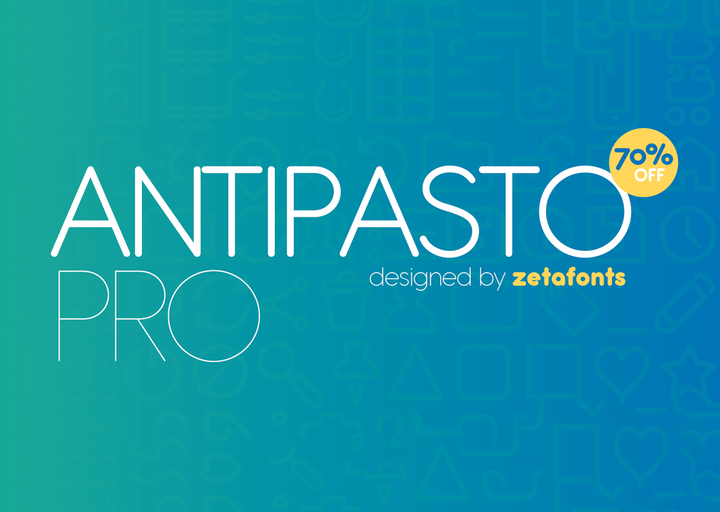
Aqui está uma descrição em português para a página de download da font Antipasto Pro Font Family: Antipasto Pro é uma nova família de fuentes gregas e cílinicas, com cinco pesos diferentes que vão desde o fino até o extrabold. Esta é a versão revista e ampliada do original lançado em 2017 pelo designer Cosimo Lorenzo Pancini. O conjunto completo agora inclui caracteres cílindricos e gregos, além de recursos typográficos avançados como minúsculas grandes e numerais antigos. Antipasto Pro também oferece 8 pesos diferentes para seus icônicos, tornando-o um recurso de design extremamente versátil. Com sua geometria pura e simplicidade, a família gera um visual moderno e eficaz sem perder seu charme distintivo. É perfeito para ambientes onde você precisa de uma fonte legível e elegante, seja em sites ou aplicativos de mídia social. Seja para design editorial ou criação de logotipos, Antipasto Pro trará um toque moderno à sua próxima peça de arte. Ao longo do tempo, a família foi ampliada e revisada com o objetivo de atender às necessidades dos designers gráficos contemporâneos. Com o antepassado original reavaliado e atualizado em 2017, Antipasto Pro é uma escolha ideal para quem busca um estilo moderno que se adapta a diferentes ambientes, desde sites profissionais até designs de logotipo. Com essa família de fuentes, você terá o poder de transformar qualquer projeto de design em algo impecavelmente moderno e elegante. Antipasto Pro é uma opção confiável para quem busca um fonte clara, moderna e versátil sem deixar de lado seu charme distintivo.